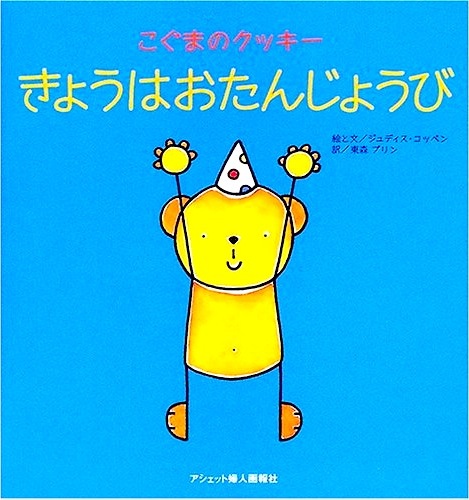
セプテンバーNは、細いペンで書いたような上品な手書き風のフォントです。デジタルフォントのツルンとしたイメージではなく、輪郭のデコボコが手書きの温もりを感じさせます。ペン習字のような気取った仕上がりではなく、手書きの味わいがある、親しみやすく、素直な気持ちが届くようなフォントです。
「セプテンバー」の新バージョンです。
看板やチラシ、雑誌、絵本、テレビやCM、アニメ、ゲームなど幅広い場面で使われています。使用例一覧が紹介されています。
作者・シリーズ | タイプラボ |